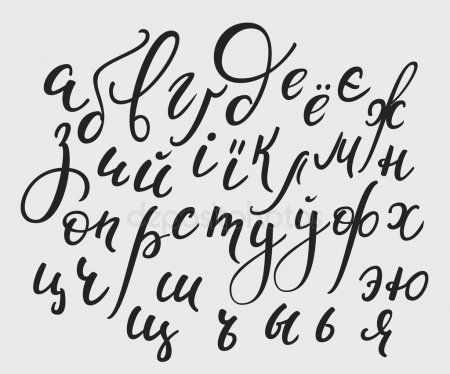
Как сделать в ворде шрифт как от руки
Как в ворде сделать шрифт от руки?
Как называется шрифт от руки?
Рукописный шрифт (скрипт) — шрифт, выполненный от руки или имитирующий его. Рукописные шрифты классифицируются в зависимости от пишущего инструмента на шрифты, имитирующие письмо ширококонечным пером, остроконечным пером, кистью и другими инструментами (карандаш, маркер, шариковая ручка и т.
Как называется рукописный шрифт в ворде?
С помощью шрифта Primo, имитирующего каллиграфическое письмо, можно самостоятельно изготовить прописи в редакторе Microsoft Word. Помимо букв русского, украинского и белорусского алфавита шрифт содержит еще соединительные линии между буквами.
Как называется шрифт прописными буквами?
Рукописный шрифт — шрифт, литеры которого выглядят как буквы написанные от руки. С помощью рукописных шрифтов имитируют надписи выполненные от руки различными пишущими инструментами — карандашом, ручкой, пером, кистью. … Все рукописные шрифты доступны для бесплатного скачивания.
Как называется шрифт курсивом?
Такой шрифт впервые получил мощное развитие в Италии эпохи Возрождения, вследствие чего в ряде языков (например, в английском и французском) курсив называется «итальянским» шрифтом (italic), в отличие от прямого «римского» (roman).
Как сделать текст в ворде пунктиром?
Подчеркнуть слова, но не пробелы между ними Выделите текст, который вы хотите подчеркнуть. Перейдите на вкладку Главная и нажмите кнопку вызова диалогового окна » Шрифт » . Перейдите к разделу Шрифт и выберите слово только в раскрывающемся списке стиль подчеркивания .
Как называется русский шрифт?
В 1708—1711 годы Пётр I предпринял реформу русской письменности, устранив надстрочные знаки, упразднив несколько букв и узаконив другое (приближенное к латинским шрифтам того времени) начертание оставшихся — так называемый гражданский шрифт.
Рукописный шрифт для Word
Привет всем читателям блога moikomputer.ru!
Хочу рассказать вам и показать на конкретном примере как сделать рукописный текст на компьютере при помощи текстового редактора Microsoft Word.
Также вы узнаете, как распечатать данный текст на принтере в формате тетрадного листа в клеточку.
Как всегда, показываю на MS 2016 так, что особенно владельцы 2003—2007 версий редактора в моем описании найдут не большие несоответствия поэтому рекомендую приобрести современный пакет продуктов Microsoft Office потому, что он реально лучше!
Прежде чем приступить к практическим действиям нужно скачать рукописные шрифты для Word, которые работают как с кириллицей, так и с латиницей, чего не скажешь о стандартных.
В сети Интернет можно найти массу предложений на скачивание разнообразных шрифтов. Но я вас избавлю от поисков по всемирной паутине сохранив ваше время и обезопасить вас, от вирусов, которые можно легко закачать вместо нужного файла особенно по незнанию.
5. Handschrift
Handschrift — это блочный рукописный шрифт с тонкими линиями, создающий впечатление письма тонким пером. Его высокая читабельность делает его подходящим, например, для подписей к изображениям на Pinterest.
6. Kalam
Kalam — это неформальный рукописный шрифт, разработанный компанией Indian Type Foundry. Он поддерживает сценарии латиницы и деванагари и оптимизирован для экранов, что придает ему плавный и сбалансированный вид. Он слегка наклонен и отлично подходит для заголовков, а также для основного текста и блок-кавычек.
7. Tragic Marker